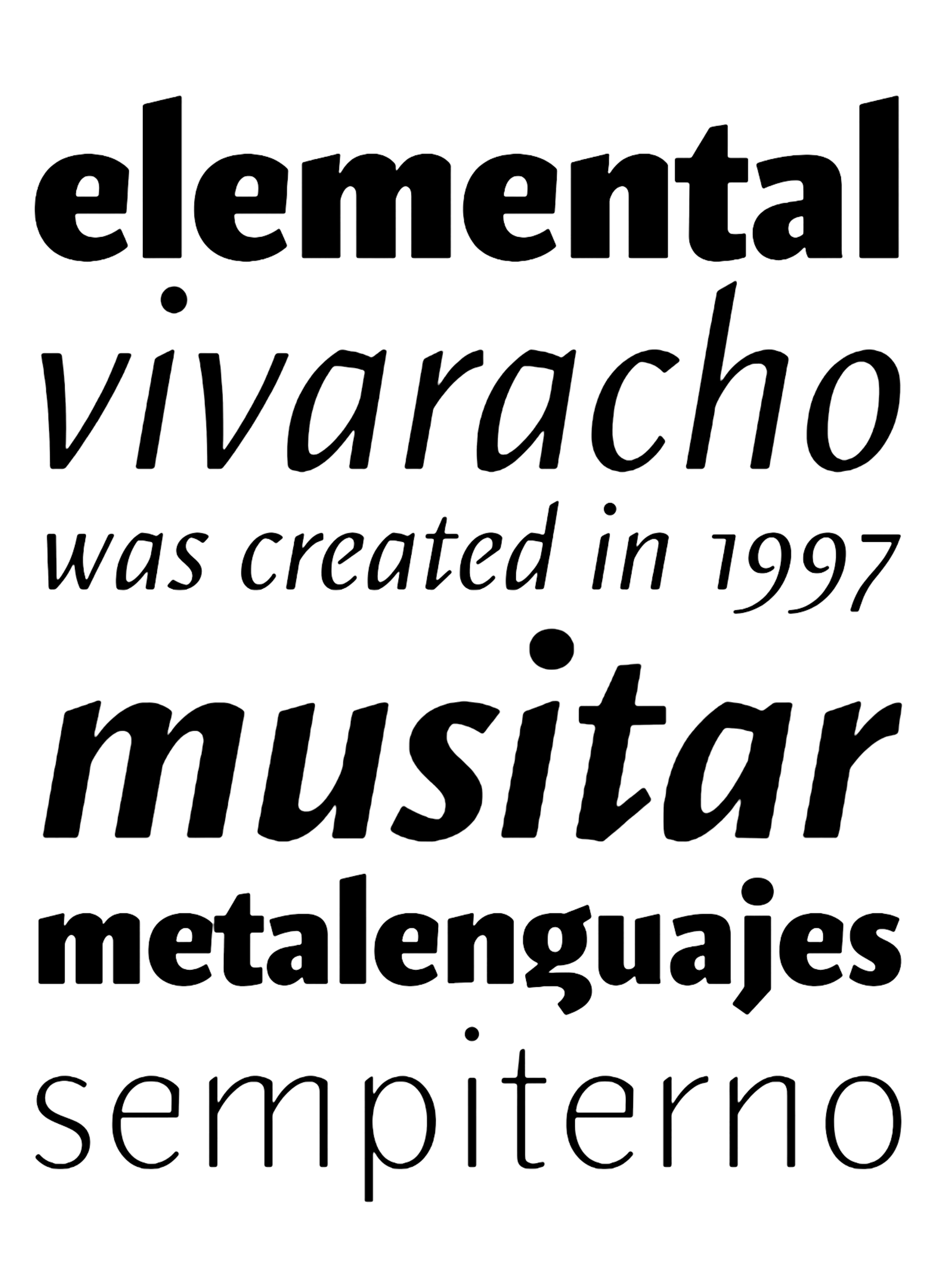
Elemental
| Año | 2001 — Actualizada: ( 2011 ) |
| Créditos | Francisco Gálvez |
| Descripción | Elemental es una tipografía creado en 1997 y lanzada en 2001. Es una Sans Serif humanista y su principal característica es un híbrido entre distintas formas de trazos caligráficos. En 2010 fue rediseñada para el bicentenario de Chile en versión Opentype y cursiva mejorada. Se ofrece en ocho pesos: Light, Regular, Bold y Extrabold y pequeñas mayúsculas para cada uno de ellos. |
| Clasificación | Texto |
| Familia(s) | Elemental Sans Pro Extra Light, Elemental Sans Pro Extra Light Italic, Elemental Sans Pro, Elemental Sans Pro Italic, Elemental Sans Pro Bold, Elemental Sans Pro Bold Italic, Elemental Sans Pro Extra Bold, Elemental Sans Pro Extra Bold Italic |
| Estilos | 8 |